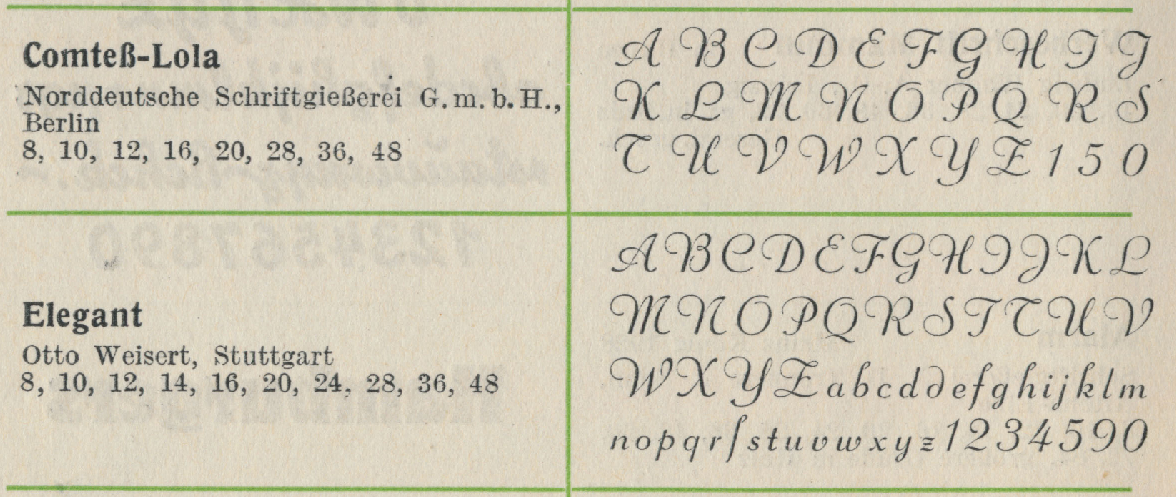
Muster Bleischrift Elegant
kann mir bitte jemand sagen, wo/wie ich ein komplettes ABC der Bleischrift
"Elegant" finde (Serifen; vermutlich Stempel AG.).
Im 2. Seemann-Nachtrag habe ich diese gefunden: Elegant von Otto Weisert, sowie deren "zwilling" Comtess-Lola bei Norddeutsche Schriftgießerei, aber eben keine Serifenschrift mit Namen Elegant. Hättest Du vielleicht ein (paar) Muster der gesuchten Schrift?